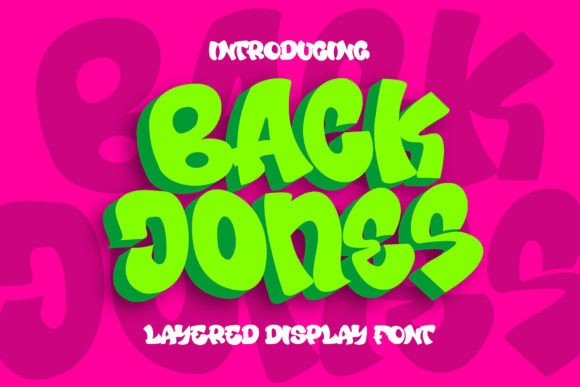
Back Jones 3d Layered
Ulasan Lengkap Back Jones 3D Layered – Font Anak yang Menggemaskan
Jika Anda sedang mencari font display yang cocok untuk proyek anak‑anak, Back Jones 3D Layered adalah pilihan yang tak boleh dilewatkan. Dengan bentuk huruf tebal, bulat, dan dilapisi tiga dimensi, font ini memberikan kesan playful sekaligus readable—dua hal yang sangat penting untuk desain yang ditujukan kepada audiens muda.
Keunggulan Utama Back Jones 3D Layered
- Karakter Tebal & Bulat: Menjamin keterbacaan yang tinggi pada ukuran kecil, ideal untuk buku cerita, poster sekolah, atau UI game anak.
- Efek 3D Layered: Menambah dimensi visual tanpa harus membuat ilustrasi tambahan, sehingga desain menjadi lebih hidup dan menarik.
- Gaya Ceria & Ramah: Membuat materi edukatif terasa lebih menyenangkan, meningkatkan motivasi belajar pada anak‑anak.
Bagaimana Back Jones 3D Layered Bekerja dalam Proyek Anda?
Berikut beberapa contoh penggunaan yang paling efektif:
- Game Edukasi: Judul level atau menu utama dengan efek lapisan tiga dimensi menambah kedalaman visual dan memandu fokus pemain muda.
- Sampul Buku Anak: Nama karakter utama ditulis dengan Back Jones 3D Layered memberi kesan “pop‑out” yang memikat.
- Materi Sekolah: Poster kelas, jadwal pelajaran, atau flyer ekstra kurikuler menjadi lebih menarik dan mudah dibaca.
- Branding Produk Anak: Logo atau tagline pada kemasan mainan, pakaian, atau perlengkapan sekolah dapat menonjol dengan sentuhan 3D.
Secara keseluruhan, Back Jones 3D Layered bukan sekadar font dekoratif—ia adalah alat yang dapat mengubah proyek desain anak menjadi lebih interaktif, mudah dipahami, dan penuh warna. Cobalah sekarang dan lihat sendiri bagaimana sentuhan tiga dimensi dapat meningkatkan daya tarik visual serta keterlibatan audiens muda Anda.